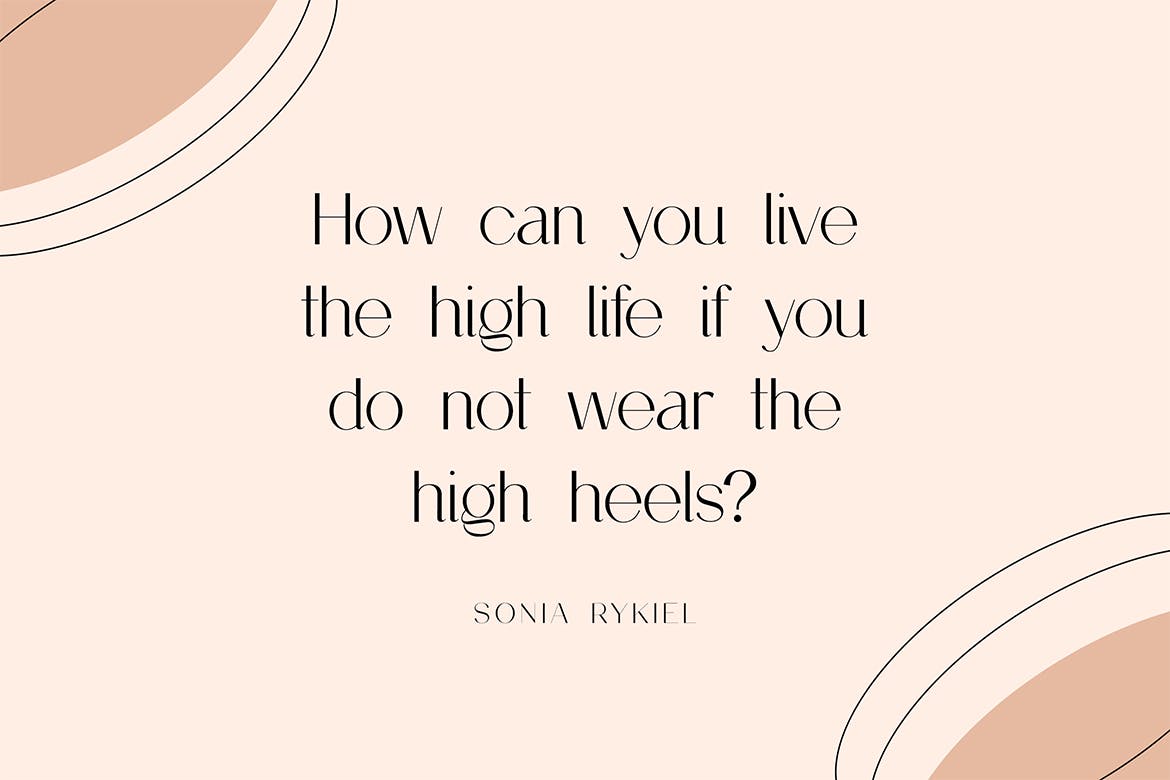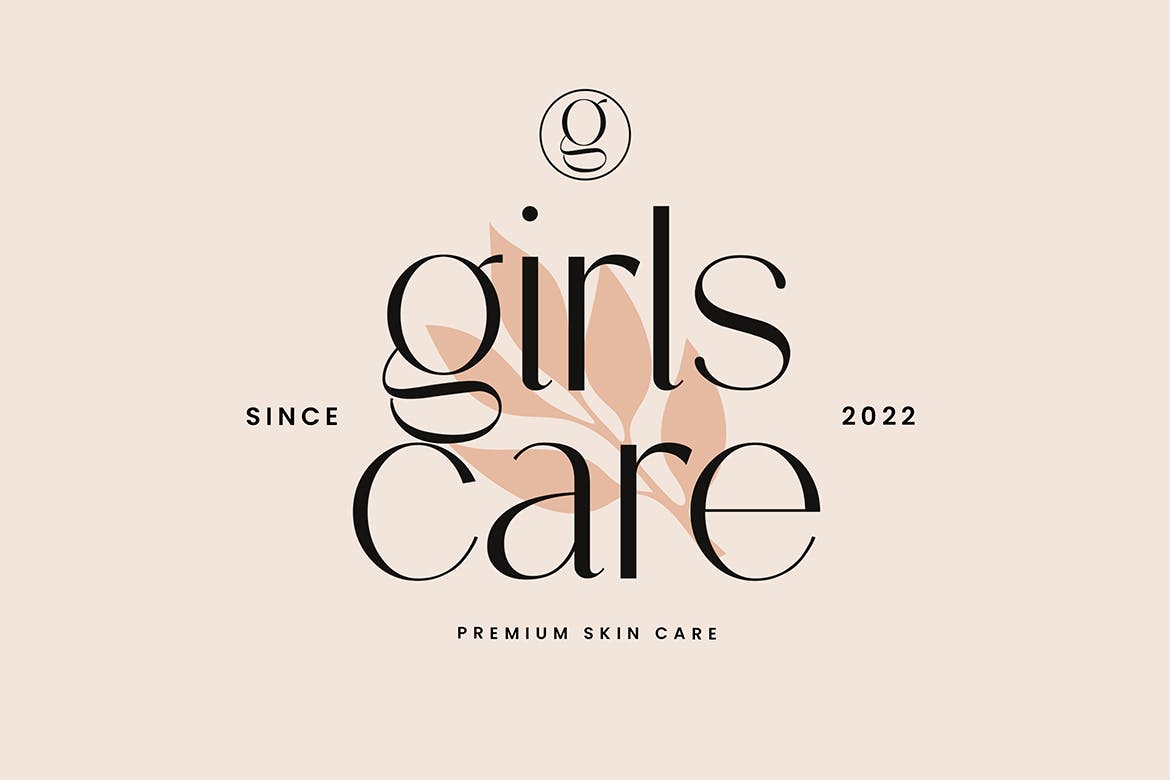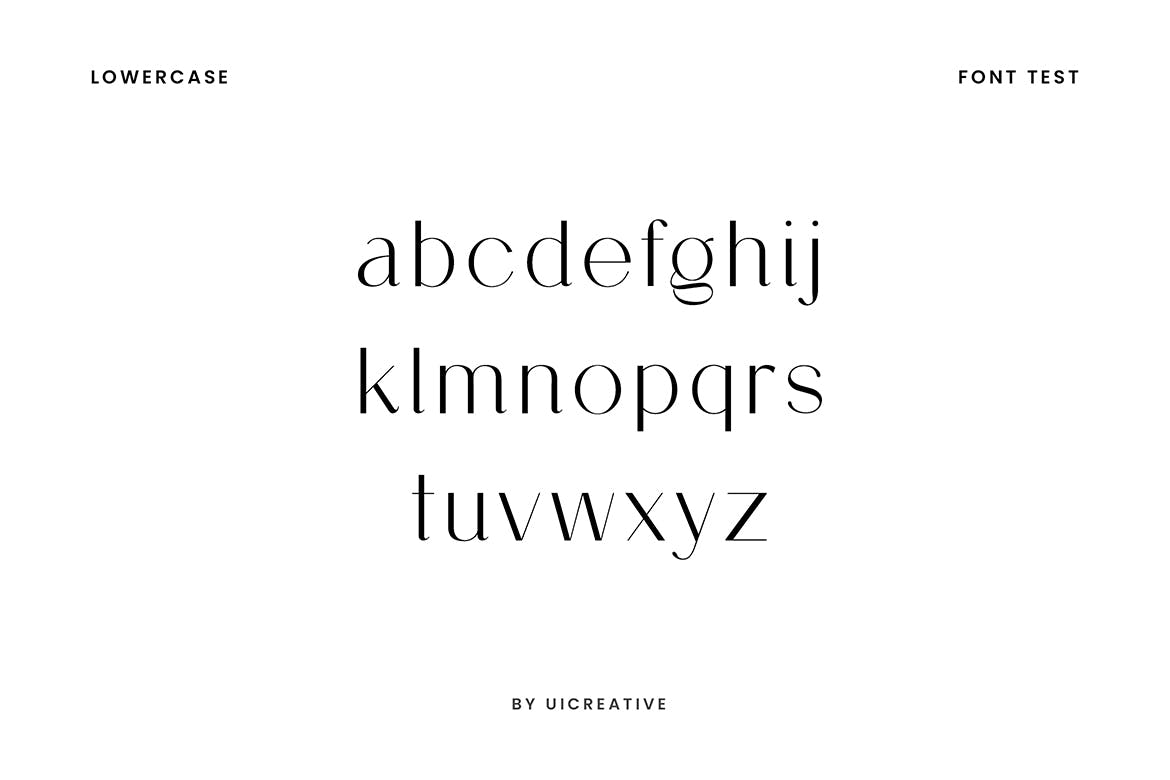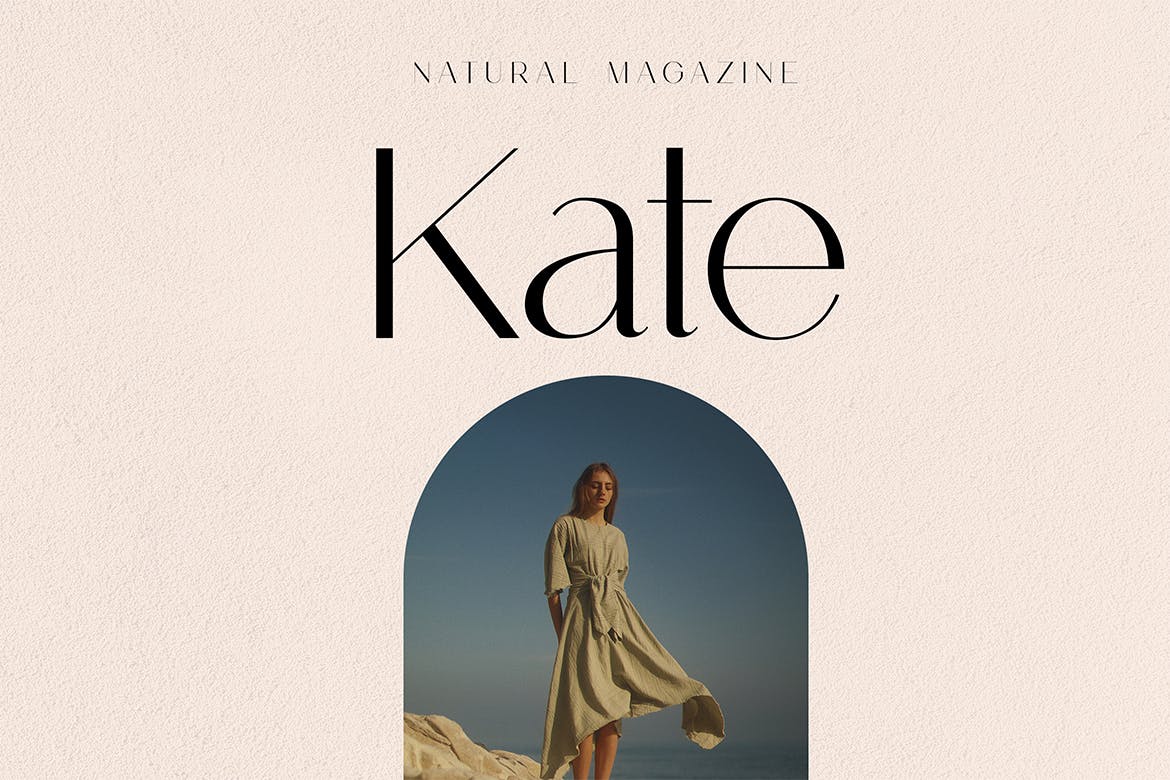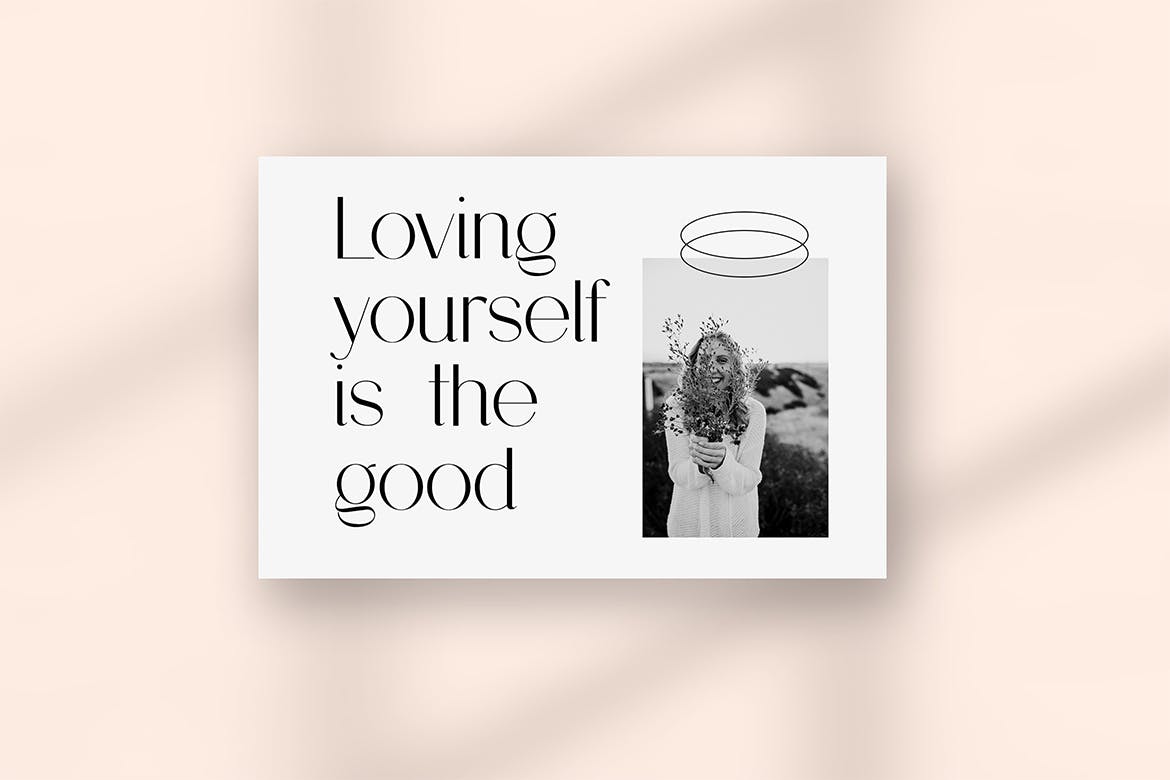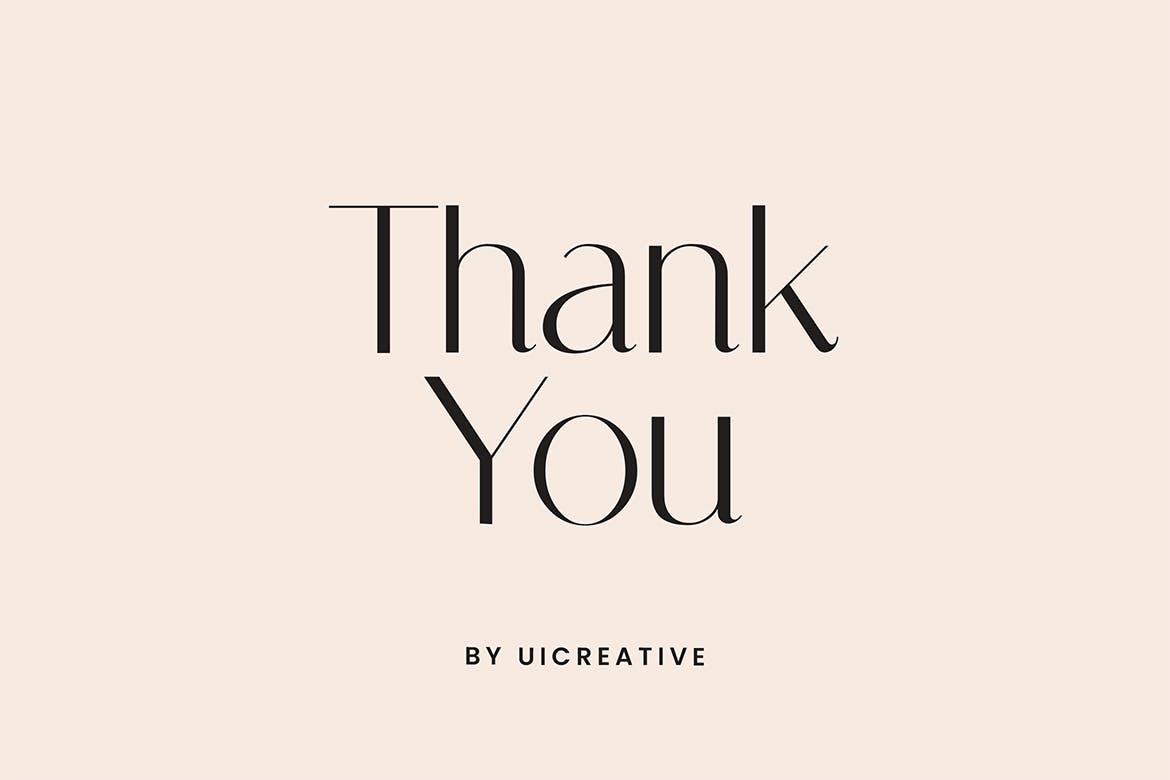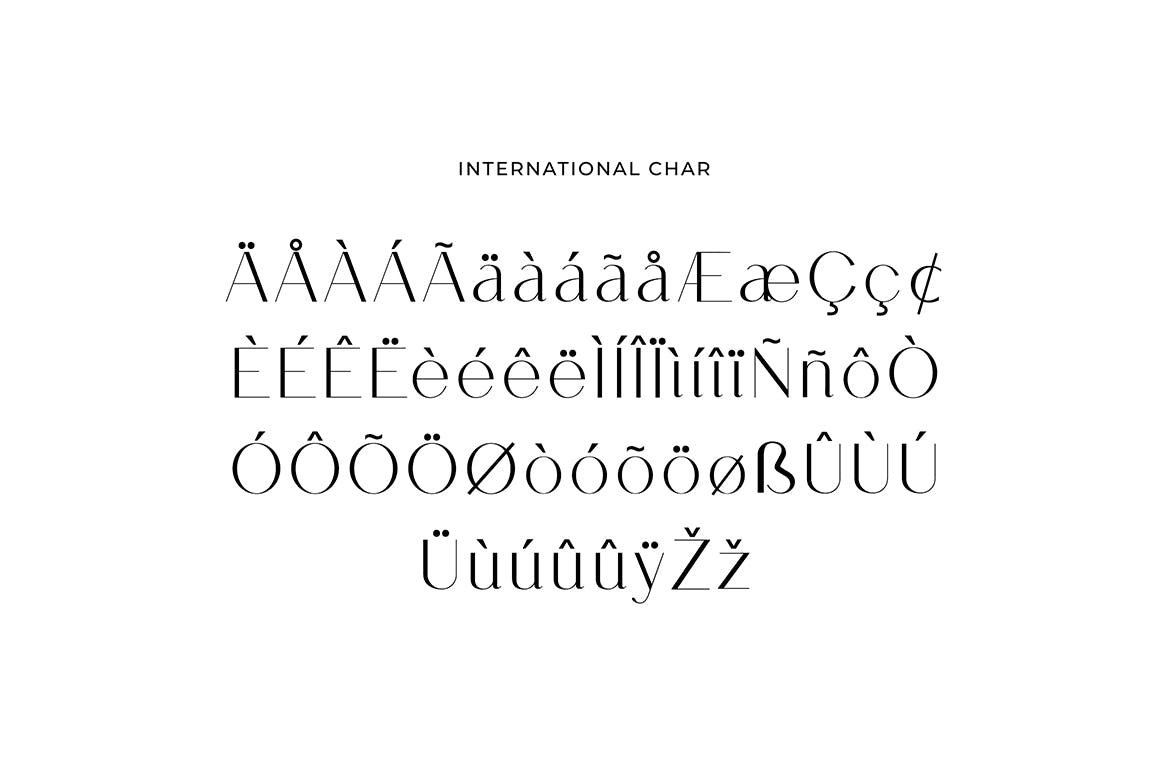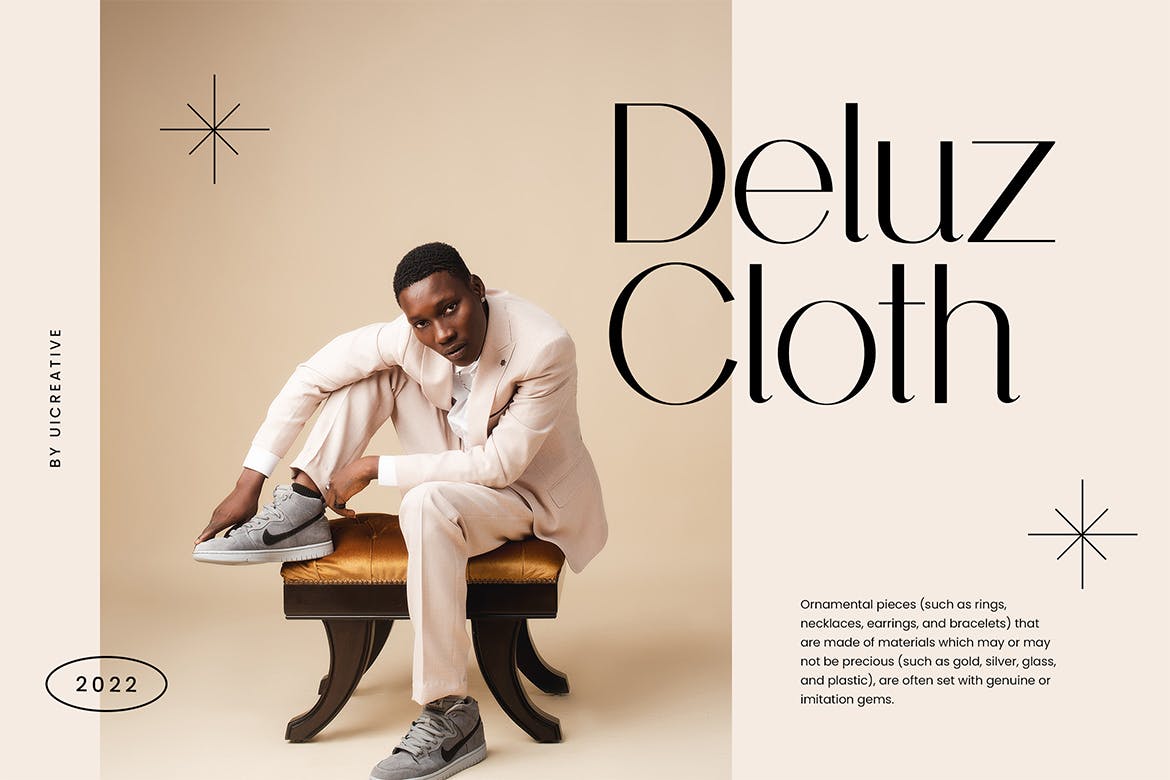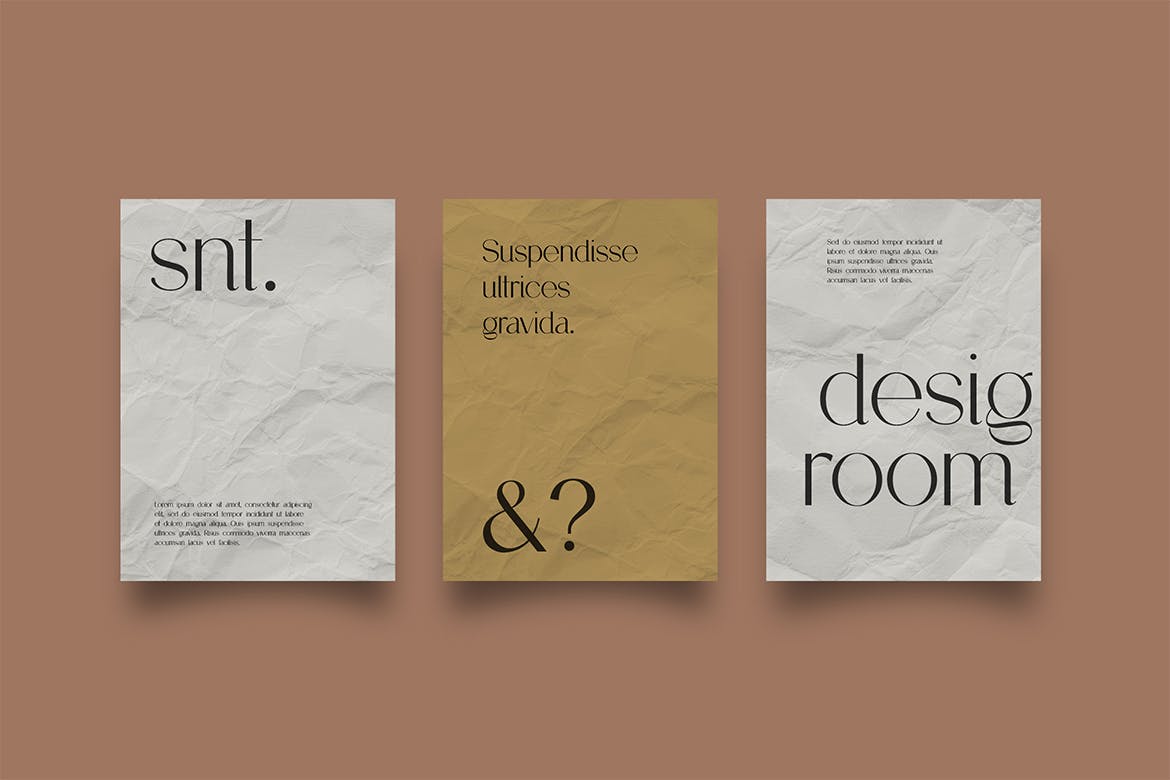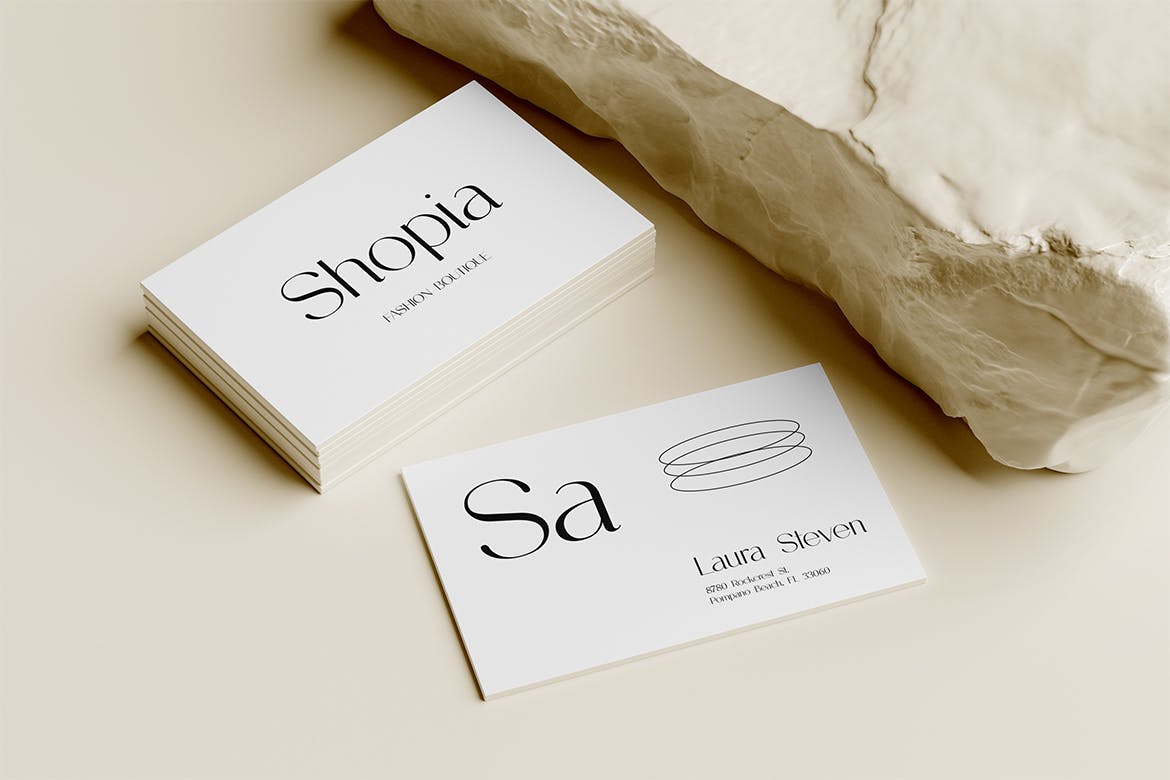
Bonnevarc Luxury Sans Serif Font
فونت Bonnevarc Luxury Sans Serif، انتخابی ممتاز برای پروژه‌های طراحی شما.
معرفی محصول جدید ما، نام آن فونت Bonnevarc Luxury Sans Serif است. این فونت سریف مدرن با ظاهری زیبا، کلاسیک، شیک و مدرن احساس می‌شود. این فونت به‌طور کامل برای پروژه‌های متنوعی از جمله امضا، لوازم اداری، لوگو، عروسی، نقل‌قول‌های تایپوگرافی، جلد مجلات یا کتاب‌ها، هدرهای وب‌سایت، لباس، برندینگ، طراحی بسته‌بندی و بیشتر مناسب است. همچنین، برندینگ مرتبط با مد یا طراحی سردبیری که هم ویژگی‌های مردانه و هم زنانه را به نمایش می‌گذارد.